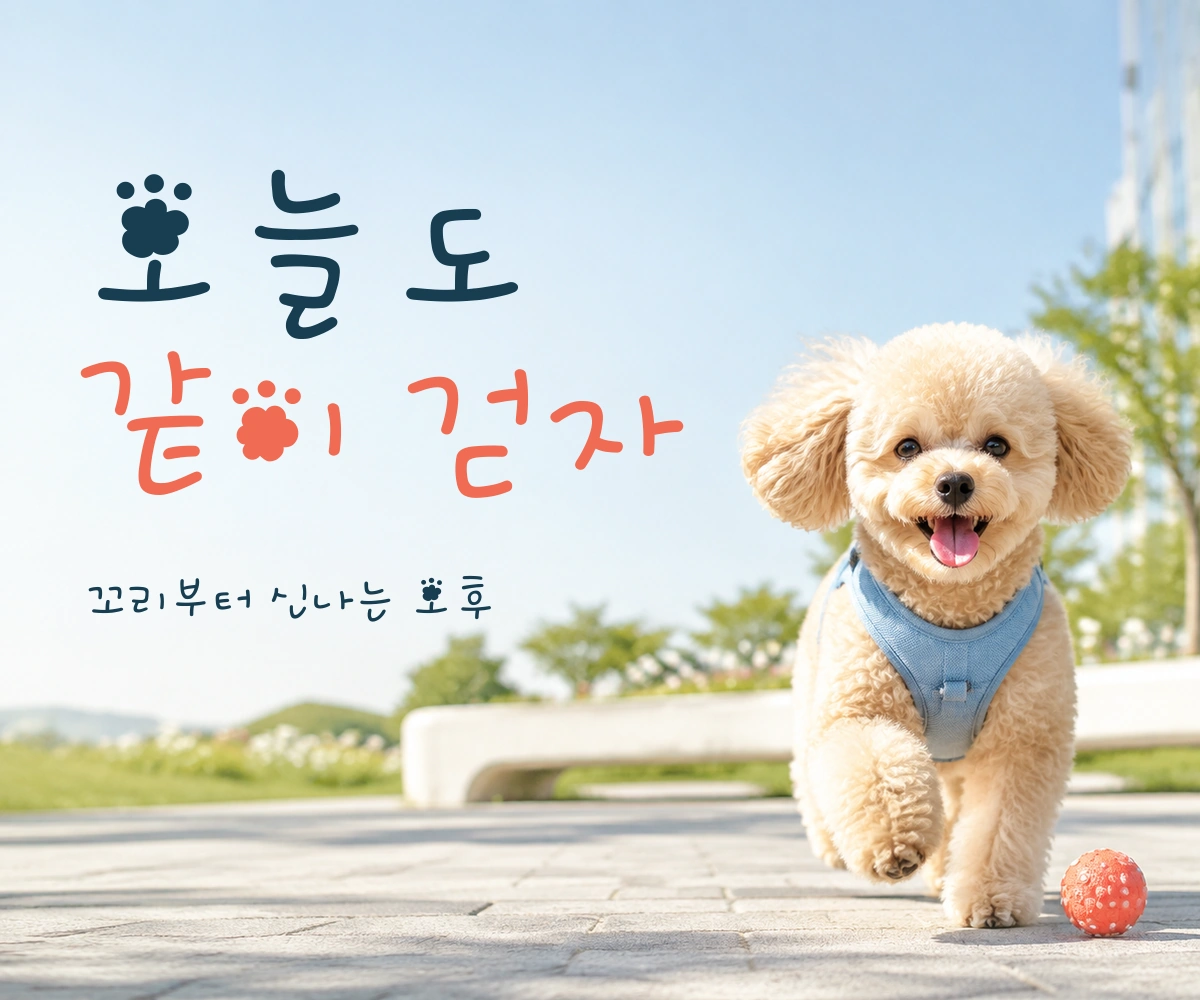
푸들 — ㈜와이즈폰트에서 배포하는 무료 폰트입니다. 획이 비는 자리마다 발바닥 자국이 찍혀 있고, 획이 아주 가벼워 산뜻하게 읽히는 손글씨체
군데군데 발바닥 자국이 찍혀 있는 손글씨 서체입니다. 랑처럼 획이 비는 자리에 발자국이 들어가 있어, 반려동물 계정 이름이나 산책·분양 안내처럼 소재가 맞는 자리에서 힘을 냅니다.
같은 회사의 손글씨 서체 가운데 가장 가볍습니다. 자면을 채우는 비율이 0.096으로 폰트픽에 올라온 같은 굵기의 한글 서체 138종 중 아래에서 열한 번째이고, 가로획이 세로획보다 1.5배 가까이 굵어 획이 옆으로 눌려 있습니다. 받침이 붙을 때 글자가 0.36em이나 아래로 내려가는 탈네모틀이라 글줄의 높낮이 차도 큰 편입니다.
획이 얇은 만큼 배경이 복잡하면 묻히니 여백을 넉넉히 두고 쓰세요. 작게 쓰면 발자국 장식도 뭉개져 알아보기 어려워지니 크게 쓰는 편이 좋습니다. 현대 한글 11,172자를 모두 담았고 굵기는 하나입니다.